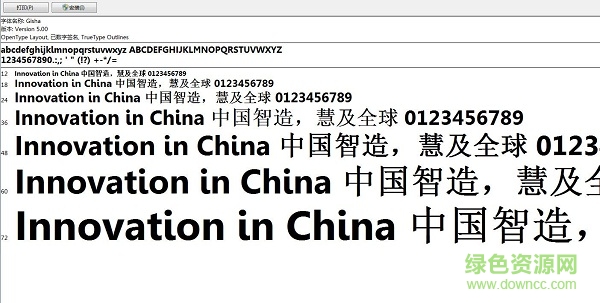
gisha bold字體
gisha bold字體是一款線條協(xié)調(diào)統(tǒng)一的英文無(wú)很想字體,字體結(jié)構(gòu)合理,字形飽滿大方,適用于計(jì)算機(jī)制作、影視字幕、平面設(shè)計(jì)以及產(chǎn)品包裝設(shè)計(jì)等領(lǐng)域,歡迎大家免費(fèi)下載!